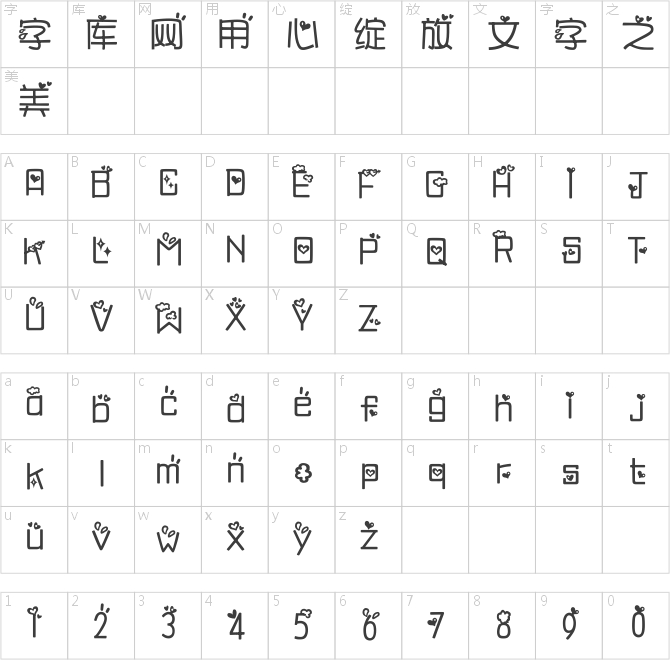
羿創(chuàng)無(wú)厘頭愛(ài)體
羿創(chuàng)無(wú)厘頭愛(ài)體字體字庫(kù)是一款讓人賞心悅目、百看不厭的中文字體,適合各類廣告和產(chǎn)品包裝設(shè)計(jì)應(yīng)用,字體大小3.57MB,格式為ttf字體,上傳用戶是哼哼哈兮,作者/版權(quán)方為羿創(chuàng)字庫(kù)